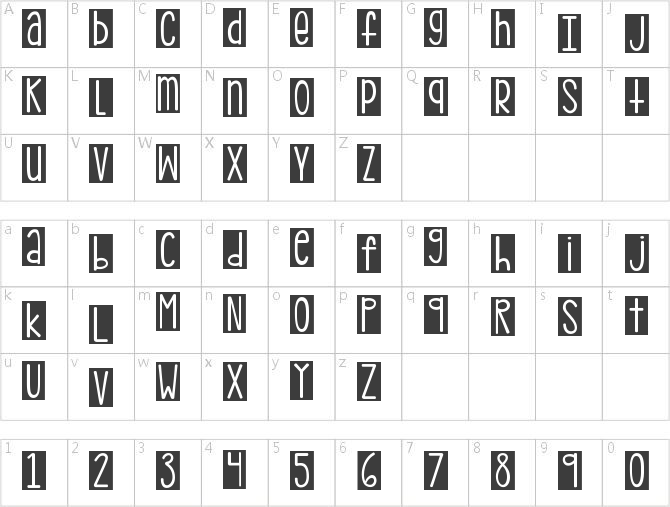
KG PDX Blocks 詳情頁(yè)
KG PDX Blocks字體字庫(kù)是一款讓人賞心悅目、百看不厭的英文字體,適合各類(lèi)廣告和產(chǎn)品包裝設(shè)計(jì)應(yīng)用,字體大小0.04MB,格式為ttf字體,上傳用戶(hù)是W^xzj,作者/版權(quán)方為未知